Es scheint, dass die meisten Puma-Teams im Jahr 2020 die gleiche Schriftart haben werden - die neue Dortmund 2020-21 Trikot-Schriftart deutet dies für uns an.
Die Schriftart für das Borussia Dortmund 20-21 Trikot ist identisch mit der von Italien und anderen Puma-Nationalmannschaften, abgesehen von ein paar geringfügigen Details.
Die Borussia Dortmund 2020-21 Schriftart verzichtet auf weitere Details und Effekte und setzt scheinbar lediglich auf ein kleines BVB-Wappen am unteren Ende.
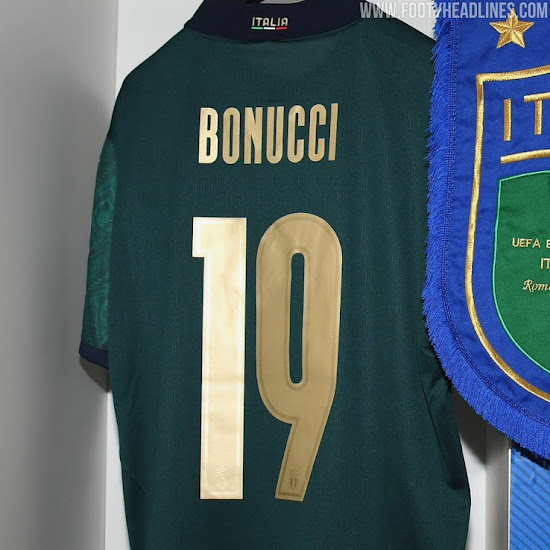
Die neue Schrift wird von Dortmund bei allen Spielen und Wettbewerben in der Saison 2020-21 eingesetzt - Bundesliga, Champions League & DFB Pokal.
Wir gehen davon aus, dass die Schriftart auch für alle anderen BVB-Trikots in der Saison 2020-2021 verwendet wird.